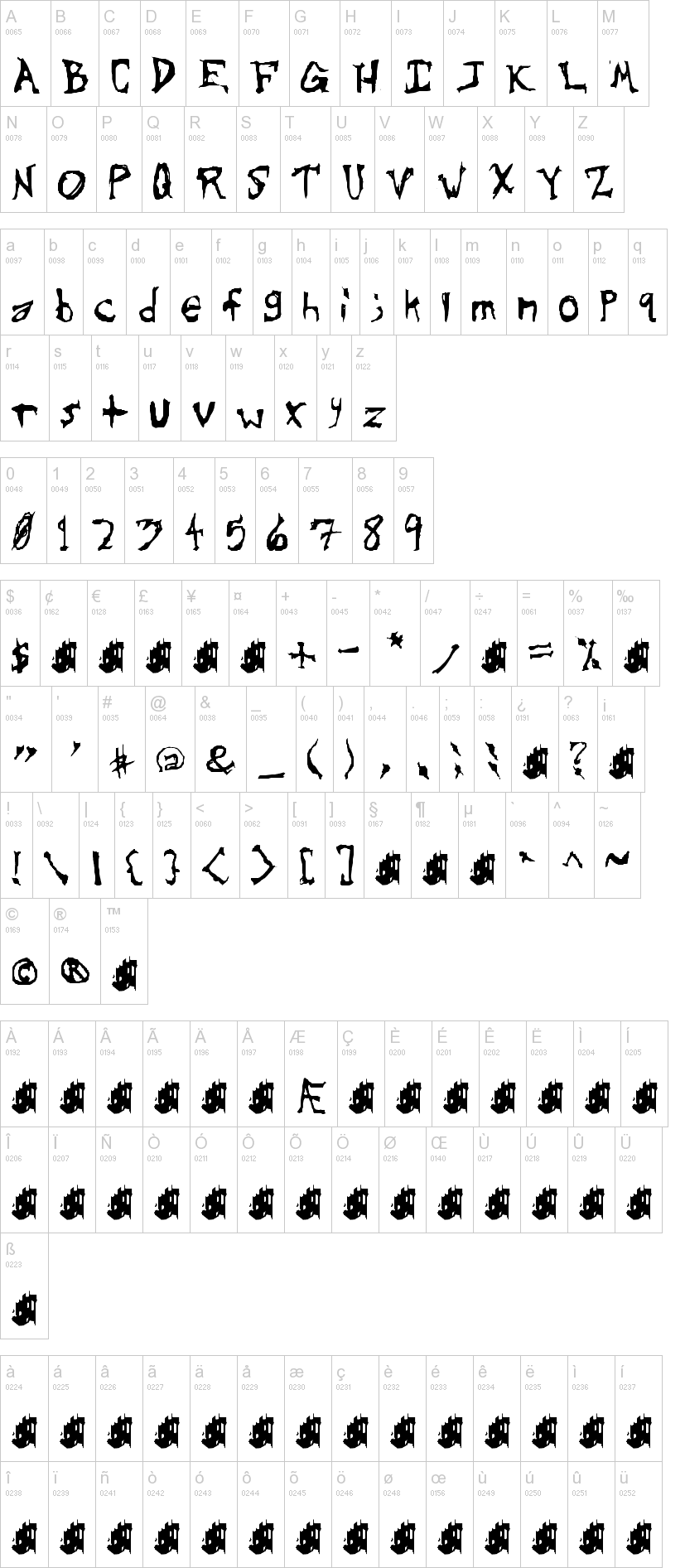
Sinister Plot 字体是一款由 Fonts of Chaos 制作的手写字体。它是一种粗犷、带有攻击性的手写字体,适用于各种媒体,包括海报、T恤、电影标题等。Sinister Plot 字体的笔画粗糙、边缘不规则,使用时能够给观众带来强烈的视觉冲击。此外,Sinister Plot 字体还具有多种字形,可以满足不同的设计需求。内容介绍
Sinister Plot是一款非常不错的手写艺术字体,具有很好的视觉感,适合于文化类的宣传设计、商业类品牌的广告和产品包装设计以及个性化文字排版等较多场景。